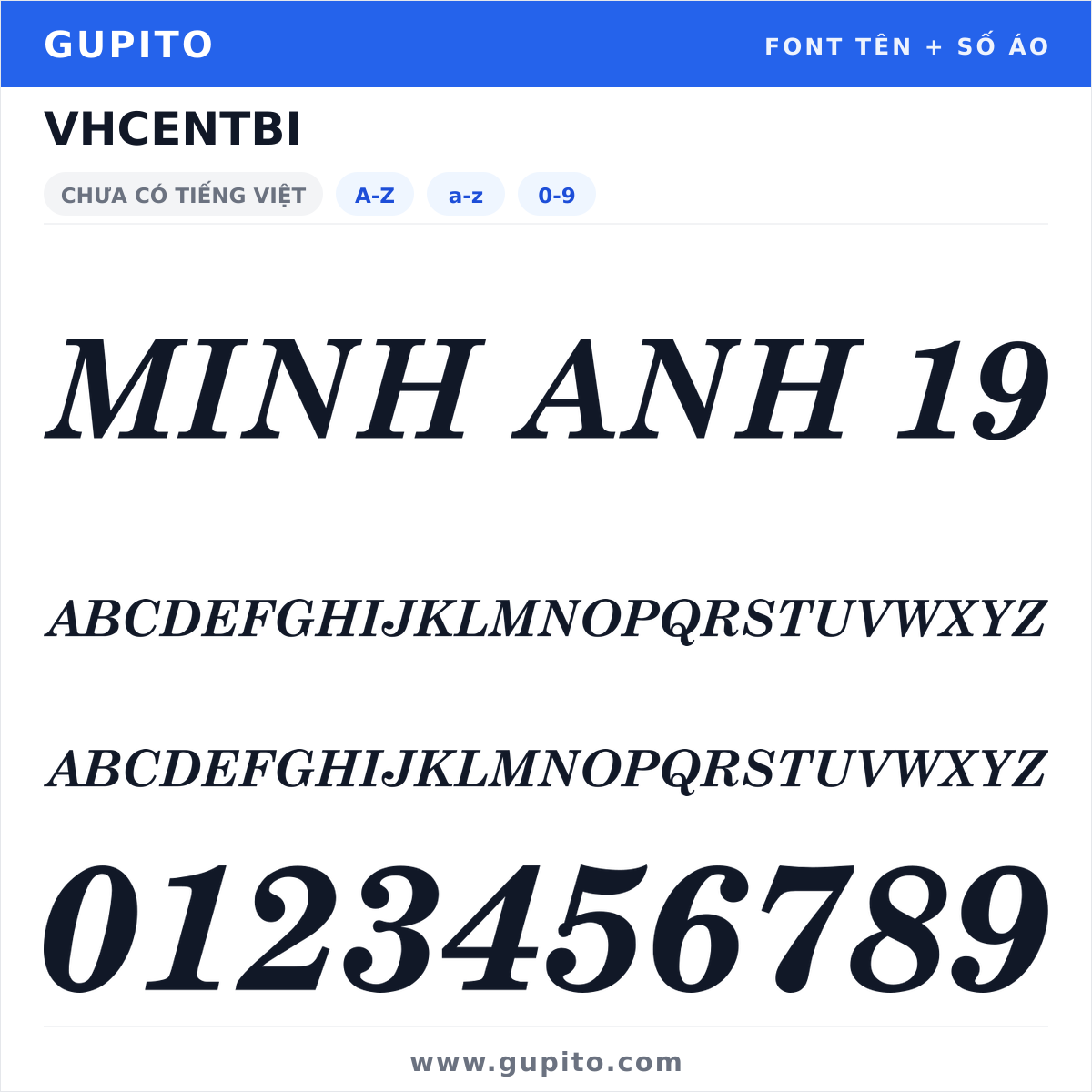
.VnCentury SchoolbookH Bold Italic
.VnCentury SchoolbookH Bold Italic · Font VHCENTBI in tên số áo bóng đá, áo lớp · chữ nghiêng chân chữ
Chưa đủ dấu tiếng ViệtA-Za-z0-9Ký tự đặc biệt
Font VHCENTBI với nét chữ đậm, chân chữ có chân, hơi nghiêng, thích hợp in tên và số áo bóng đá, áo lớp, quà tặng. Bộ chữ .VnCentury SchoolbookH Bold Italic dùng để in chuyển nhiệt lên áo đấu, áo lớp, áo nhóm và đồ thể thao theo yêu cầu. Kiểu dáng: chữ nghiêng chân chữ. Font dùng cho chữ không dấu và số áo. Có đủ bộ chữ số để in số áo. Từ khoá liên quan: font vhcentbi, font in tên áo, font in số áo, font áo bóng đá, font áo lớp, font thể thao, font chữ nghiêng, font có bảng số.